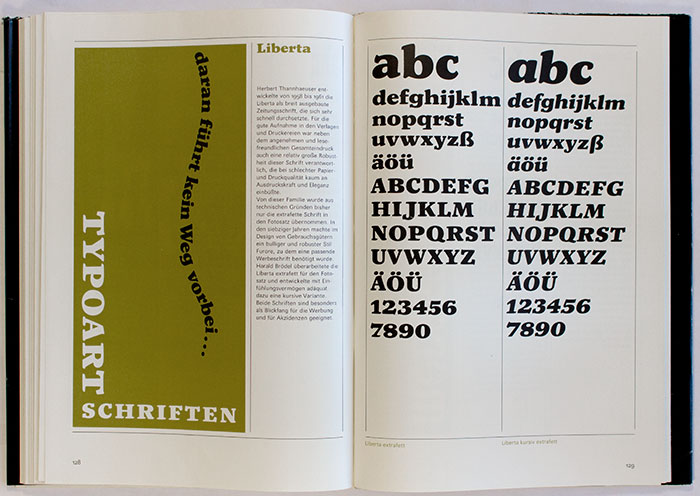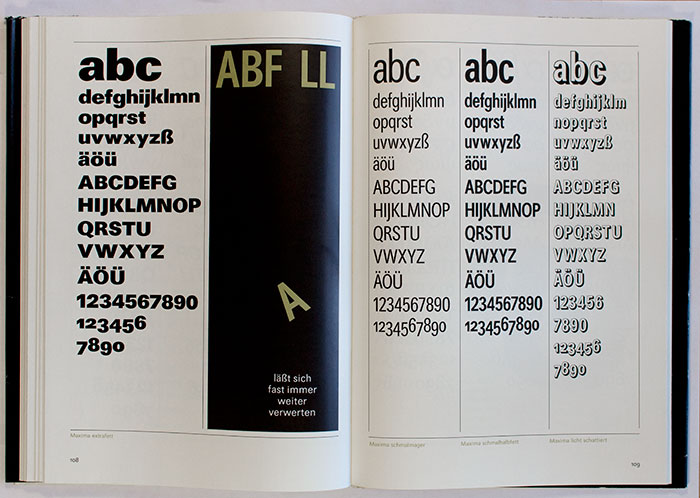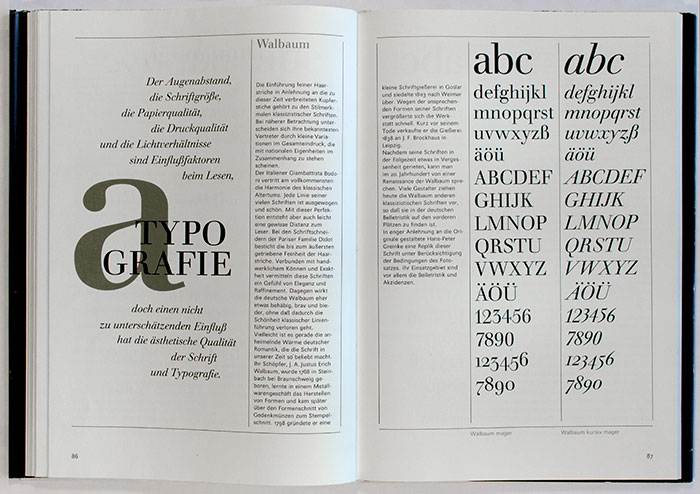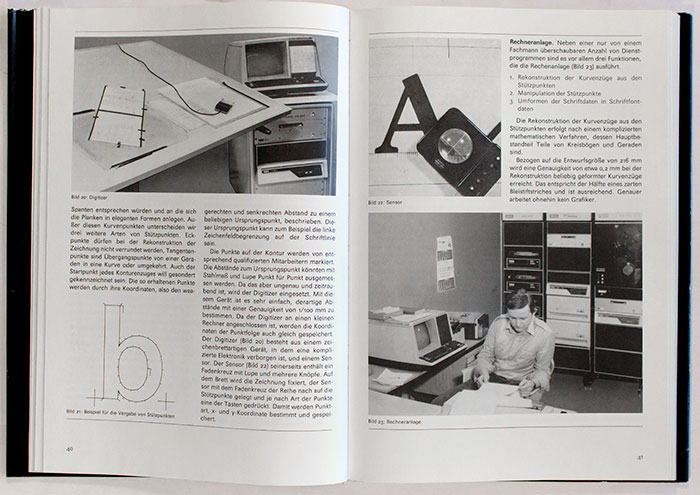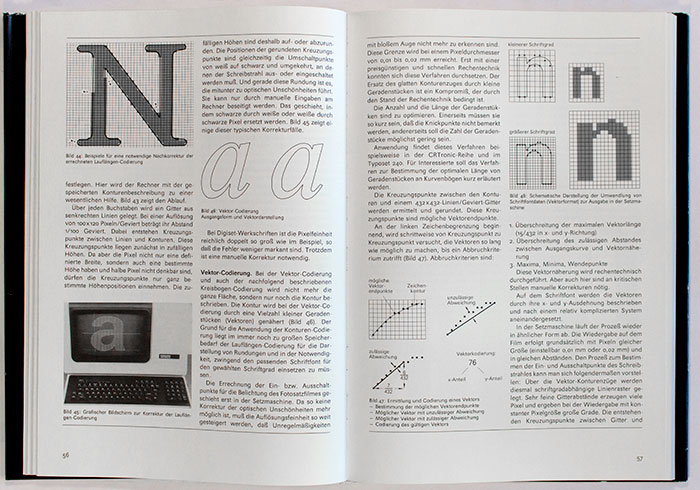
Das Buch Fotosatzschriften kann als ein Nachfolger des Buches »Typoart Typenkunst« angesehen werden. Während letzteres das Schriftschaffen in der DDR Anfang der 1970er-Jahre beschrieb, widmet sich das Buch Fotosatzschriften der Technik und den DDR-Schriften Ende der 1980er-Jahre.
Die ersten 50 Seiten des Hardcover-Buches widmen sich der Technik des Fotosatzes und wie mit ihm bei Typoart Schriften entworfen wurden. Auch die gestalterischen Aspekte des Schriftentwurfs und -ausbaus werden dabei ausführlich beleuchtet. Den größten Teil des Buches (mit knapp 100 Seiten) machen dann die Schriftvorstellungen von Typoart-Fotosatz-Schriften aus. Dabei werden die Schnitte der einzelnen Familien gegenübergestellt und ein Beschreibungstext gibt Auskunft über den Entwurf.
Inhaltsverzeichnis:
- Vorwort
A – Schriftherstellung in der DDR
- Was brachte der Übergang zum Fotosatz für die Schriftqualität
- Neue Zielvorstellungen in der DDR
- Lesbarkeit, Schönheit, Charakter
- Schriftfamilien
- Wieviele Basisgrade sind notwendig?
- Welche Zeichen gehören zu einem Sortiment?
- Kyrillische und griechische Schriften
- Der Type-Designer und seine Motivationen
- Vom Prokrustesbett des Type-Designers
B – Schriftherstellung
- Schriftkonzeption
- Normierungen
- Orientierungshilfen
- Rechnergestützte Zeichenanlage
- Arbeitsstufen der Schriftentwicklung
- Schnittausbau
- Erweiterungen zum Sortiment
- Ergänzende Angaben zu den Schriften
C – Schriftfonts
- Digitale Beschreibungsformen
- Fotosatz und Qualität
D – Schriftbeispiele
Untertitel: Typedesign + Schrifthersteller
Autor(en): Detlef Schäfer
veröffentlicht: 1989
Verlag: VEB Fachbuchverlag Leipzig